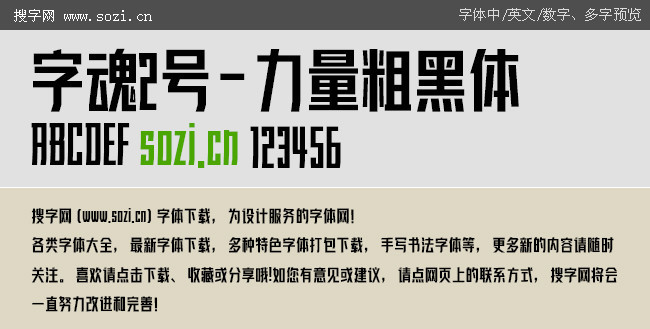
字魂2號-力量粗黑體
搜字網(wǎng)提供一款字魂2號-力量粗黑體中文字體下載,字魂2號-力量粗黑體字體是一款無襯線體字體,該字體包含6763個中文、字母、 符號和數(shù)字,具有有力、穩(wěn)重、堅硬、現(xiàn)代、簡約 的風(fēng)格,可以滿足您設(shè)計上的各種需求,該字體主要用于海報企宣、正文、書籍、報紙、健康養(yǎng)生 等場景。